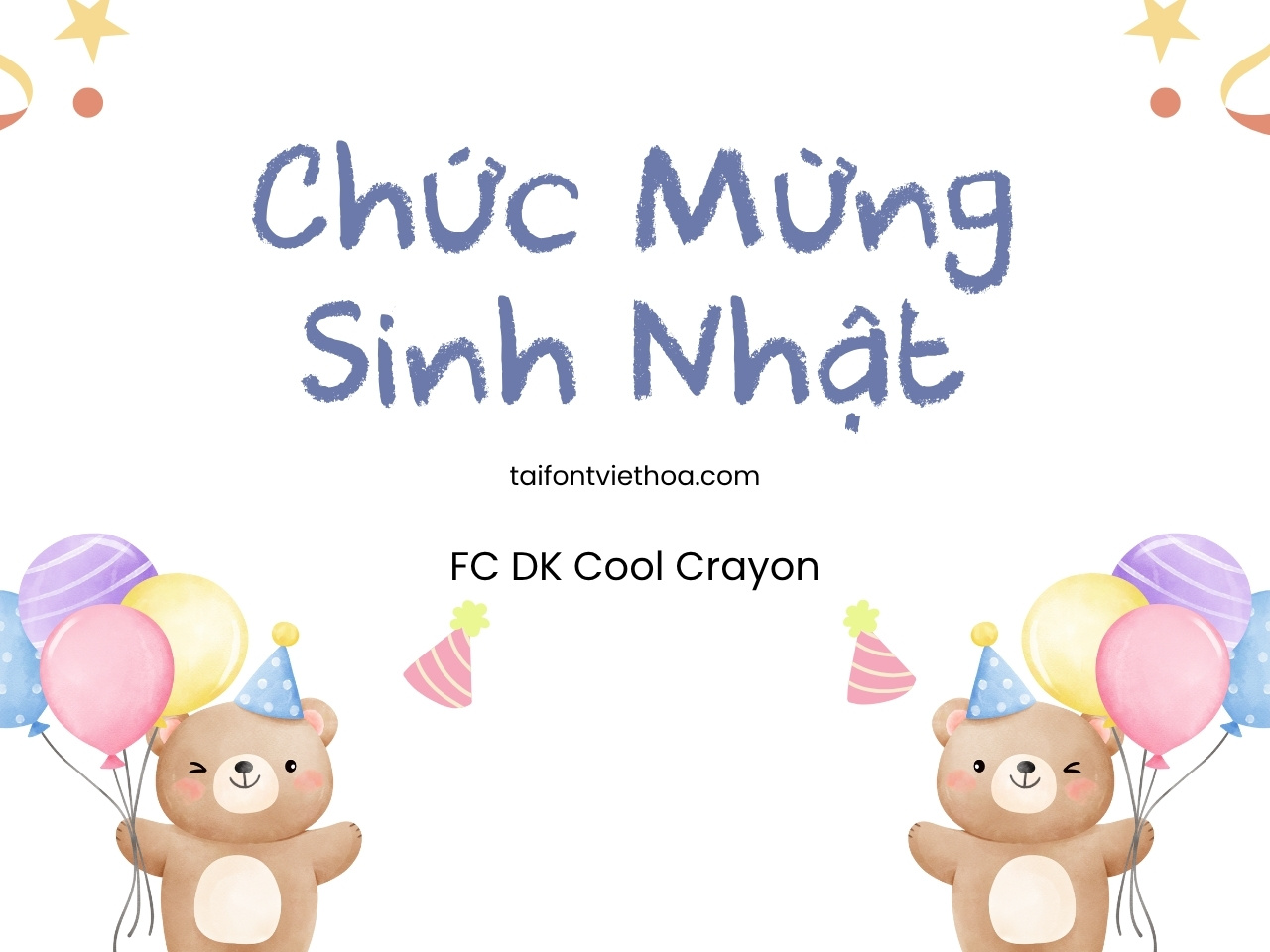
Font việt hóa FC DK Cool Crayon
Tác giả Font: David Kerkhoff
Giới thiệu về font DK Cool Crayon và phiên bản Việt hóa
FC DK Cool Crayon là phiên bản Việt hóa từ font gốc DK Cool Crayon – một thiết kế viết tay nổi bật của David Kerkhoff, nhà thiết kế người Hà Lan chuyên sáng tạo các kiểu chữ phá cách, mang tính cá nhân cao. Font mô phỏng cảm giác viết bằng bút sáp màu (crayon) với các đường nét hơi thô ráp, sinh động và tự nhiên, rất phù hợp trong các thiết kế dành cho trẻ em, giáo dục, sản phẩm thủ công hoặc truyền thông sáng tạo. Font gốc được phát hành qua Hanoded Fonts và hỗ trợ hơn 50 ngôn ngữ nhờ bảng ký tự Latin mở rộng.
Khác với phiên bản “1FTV VIP DK Cool Crayon” từng được giới thiệu trước đó, FC DK Cool Crayon là một bản Việt hóa riêng biệt do cộng đồng Font Chuẩn thực hiện. Phiên bản này được bổ sung đầy đủ hệ dấu tiếng Việt theo chuẩn Unicode, đồng thời giữ nguyên hiệu ứng “phấn màu” ngộ nghĩnh và phong cách viết tay gần gũi của bản gốc.
Đặc điểm thiết kế và ứng dụng của FC DK Cool Crayon
FC DK Cool Crayon sở hữu những nét viết mềm, uốn cong không đều, tạo cảm giác chân thật như được vẽ tay bằng phấn sáp. Đặc điểm nhận diện là các đường viền thô nhẹ, bố cục ký tự không đồng nhất – điều này giúp tăng tính sinh động và gợi cảm giác vui tươi, hồn nhiên. Chữ thường và chữ hoa được thiết kế đồng đều, phù hợp cho cả tiêu đề và nội dung ngắn.
Font này lý tưởng cho các dự án giáo dục trẻ em, bìa sách thiếu nhi, poster học tập, bảng tên lớp học, đồ chơi handmade, thiết kế hoạt hình và các sản phẩm truyền thông dành cho trường mẫu giáo, nhà sách, hoặc thương hiệu liên quan đến trẻ nhỏ. Ngoài ra, DK Cool Crayon cũng rất phù hợp trong các thiết kế viral mang tính giải trí nhẹ nhàng, dễ chia sẻ trên mạng xã hội.